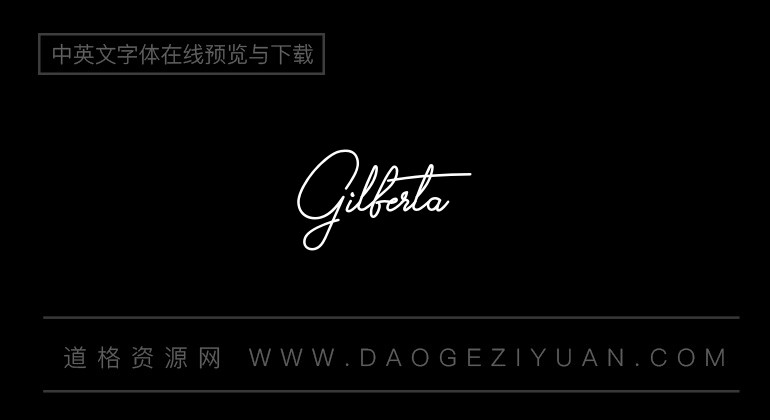
Gilberta
Gilberta是一款现代古典的字体,由著名设计师Gilbert Baker设计。它具有传统古典风格的精致细腻,但又具有现代风格的简洁、灵活,能够满足多种应用场景的要求。它的字体特点是拥有极其优雅的笔画,在阅读体验上非常细腻,能够给人以舒适的感受,是一款非常适合用于报刊、书籍、杂志、广告、海报等等等等的字体。
Gilberta是一款非常不错的手写艺术字体,具有很好的视觉感,适合于文化类的宣传设计、商业类品牌的广告和产品包装设计以及个性化文字排版等较多场景。